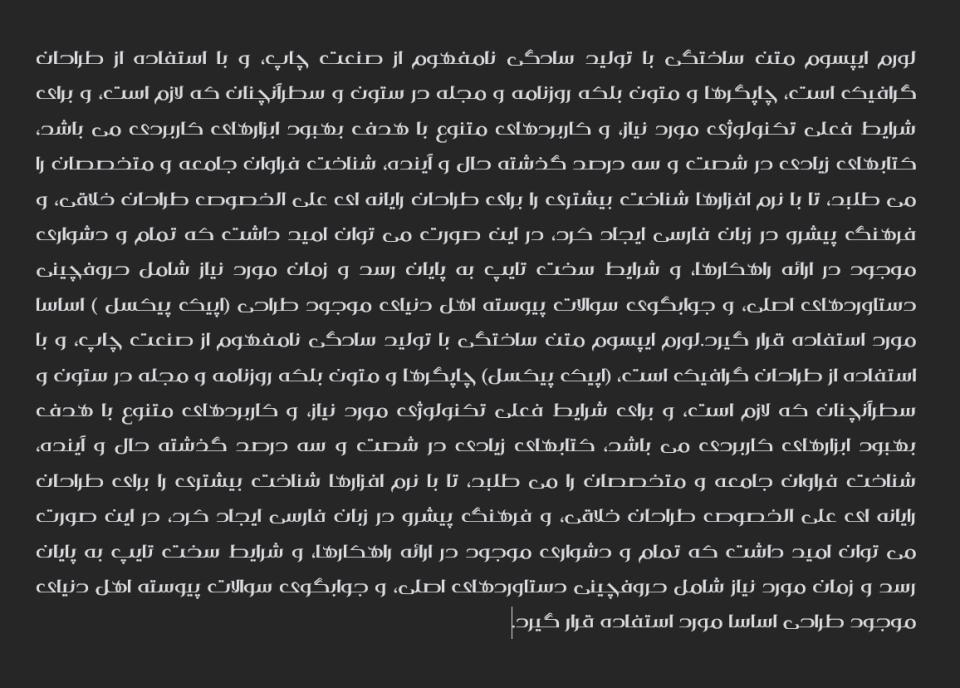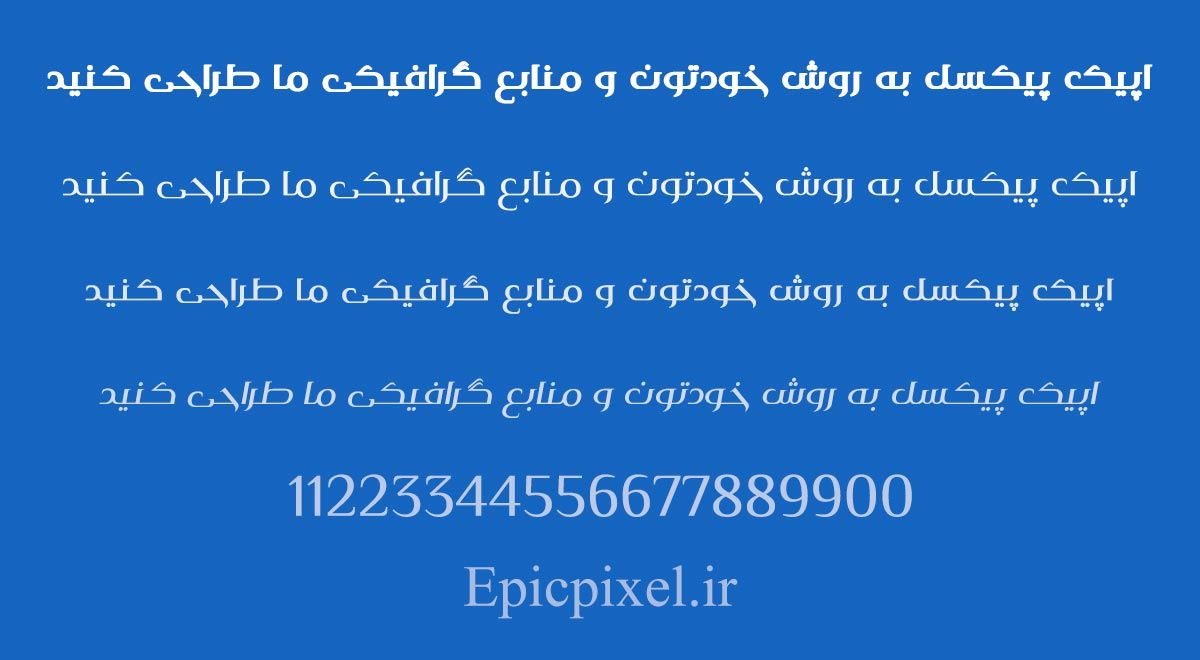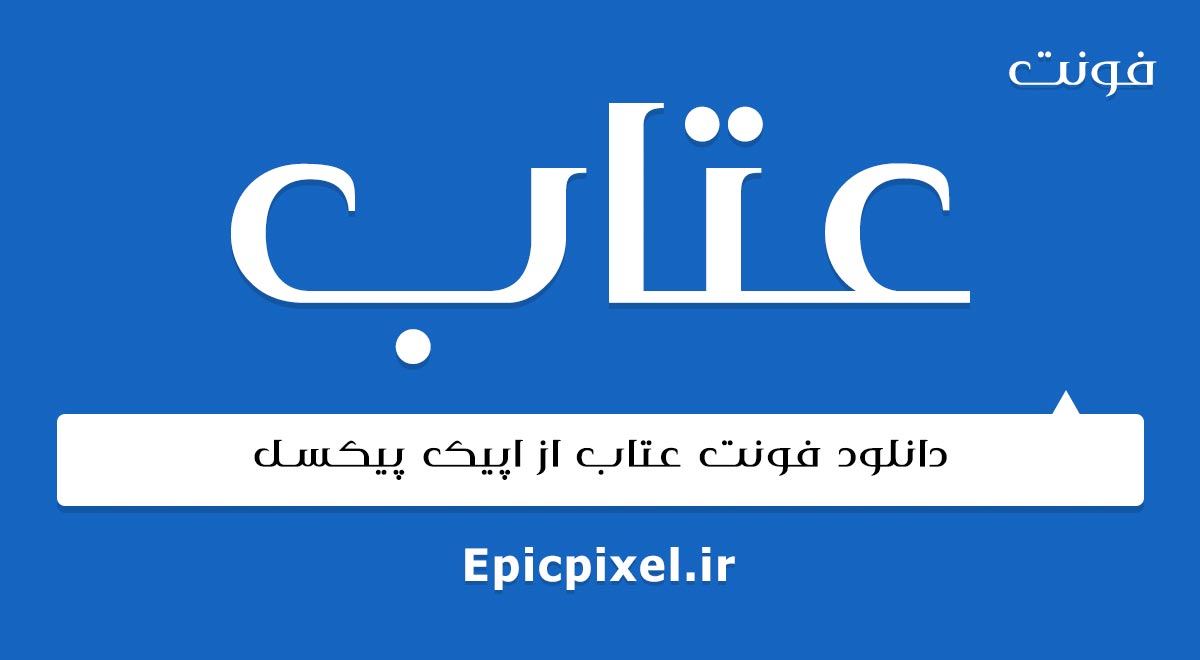
۳ فونت عتاب فارسی Etab
چرا فونت عتاب فارسی را دانلود کنیم؟ این سوالی است که شاید برای هر طراح و گرافیستی پیش بیاید. فونت عتاب، با وجود ریشه های عربی، به خوبی با زبان فارسی سازگار شده و می تواند جلوه ای خاص به نوشته های شما ببخشد.
یکی از ویژگی های بارز این فونت، ساختار هندسی و در عین حال نرم آن است که باعث می شود هم در عناوین بزرگ و هم در متن های کوتاه، خوانایی بالایی داشته باشد. این ویژگی به خصوص برای طراحی پوستر، لوگو و بسته بندی بسیار مفید است. در واقع، عتاب با خطوطی که نه خیلی خشک و نه خیلی گرد هستند، تعادلی زیبا ایجاد می کند.
شاید بتوان گفت یکی از محدودیت های این فونت، عدم تنوع زیاد در وزن ها و استایل ها باشد. یعنی شما گزینه های زیادی برای ضخامت یا حالت مورب (ایتالیک) ندارید. اما همین سادگی، باعث تمرکز بیشتر بر فرم اصلی فونت و ایجاد هماهنگی در طراحی می شود. در نتیجه، اگر به دنبال یک فونت ساده، شیک و خوانا برای پروژه های فارسی خود هستید، فونت رایگان عتاب می تواند انتخاب بسیار خوبی باشد. این فونت به دلیل ساختار منسجم خود، در طراحی های مدرن و سنتی به خوبی می نشیند و به نوشته های شما هویتی خاص می بخشد.